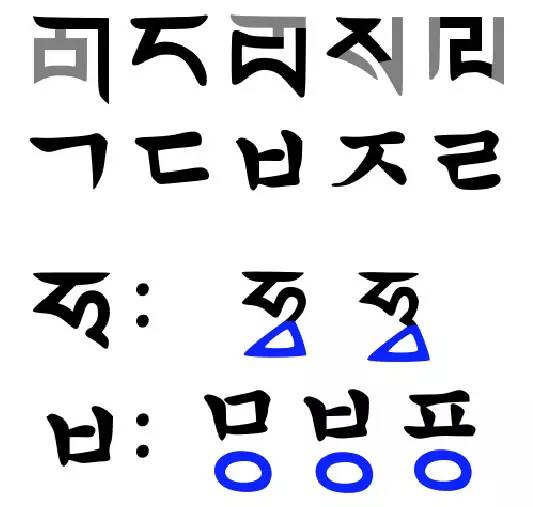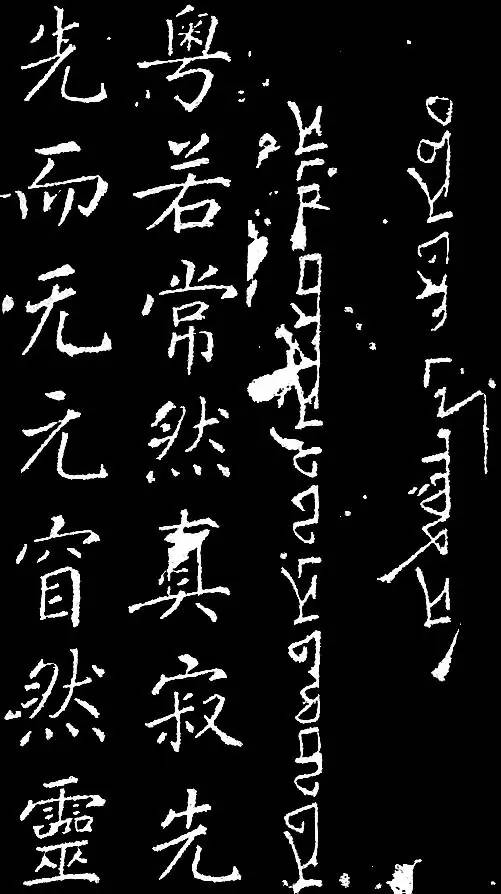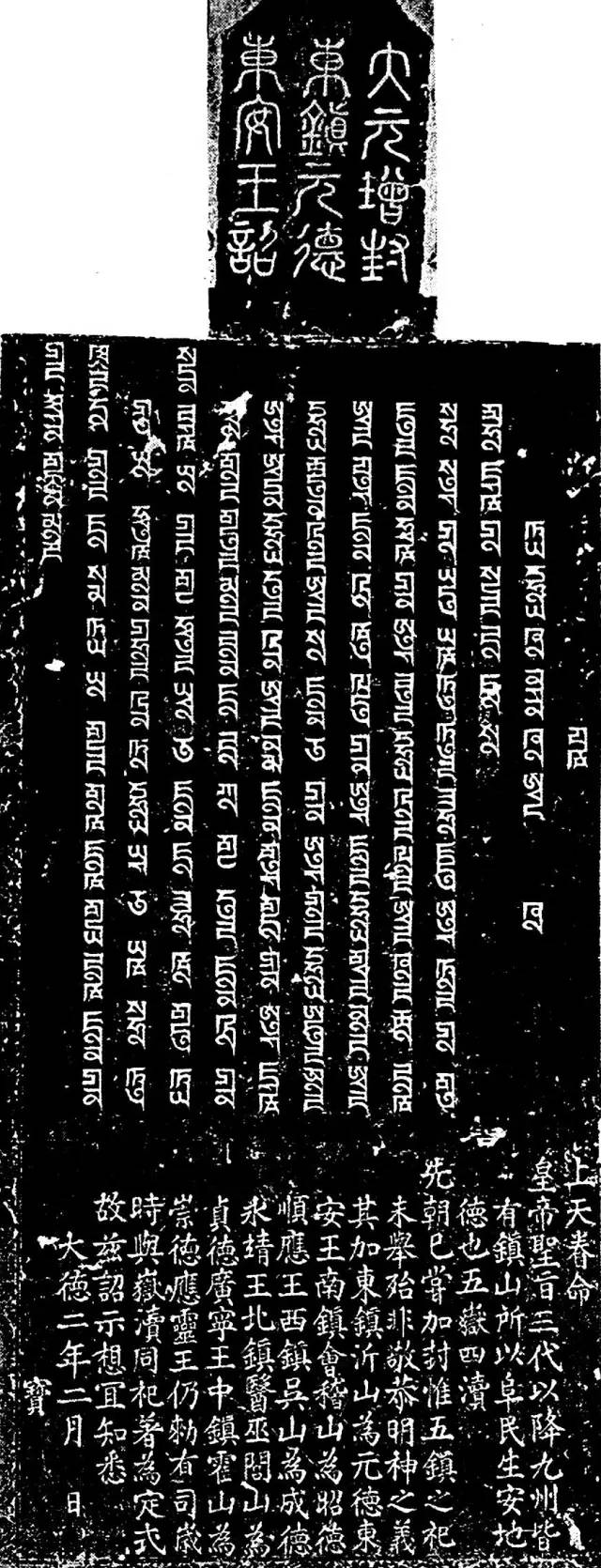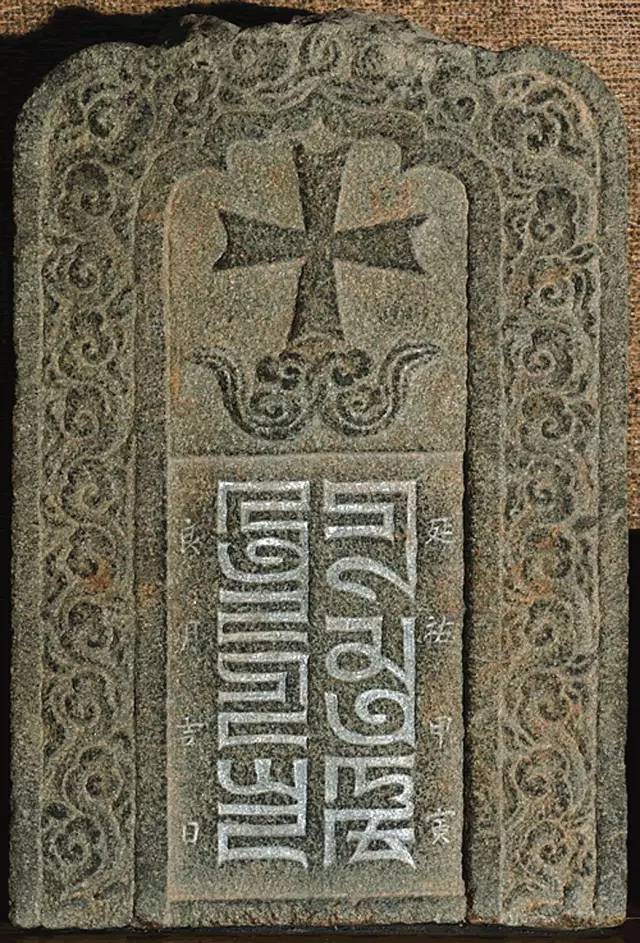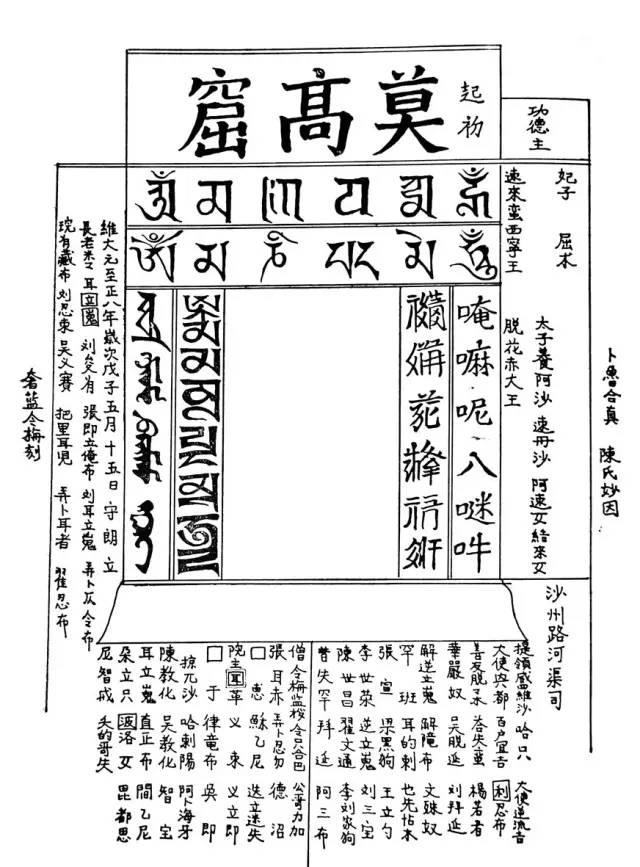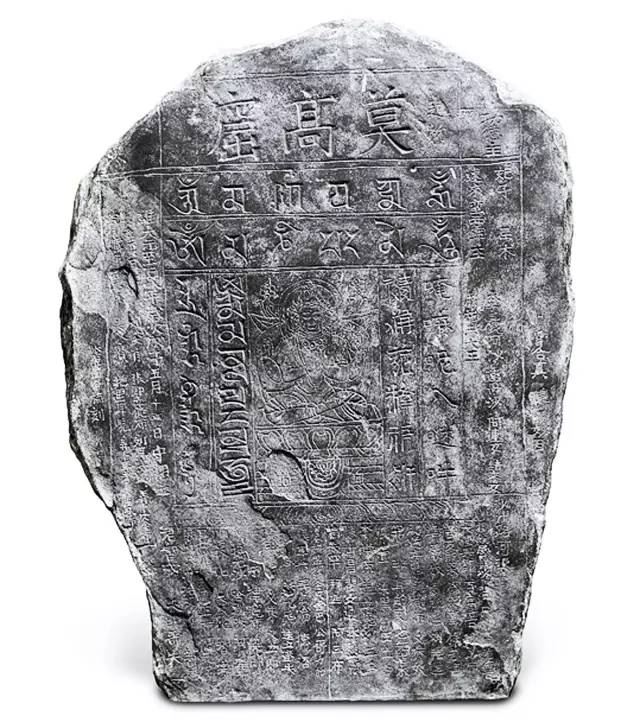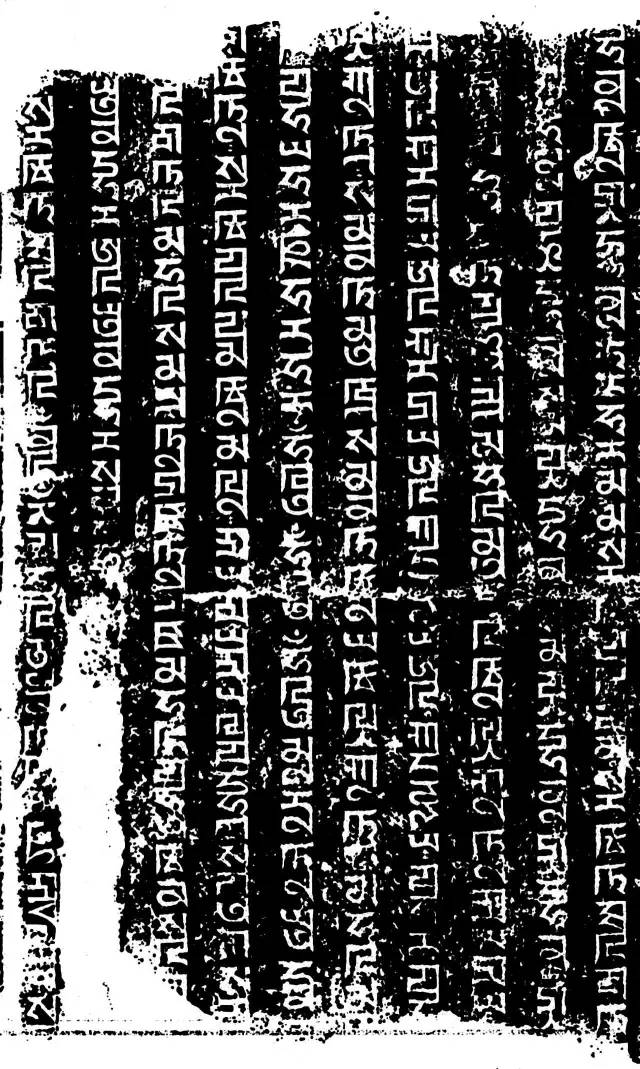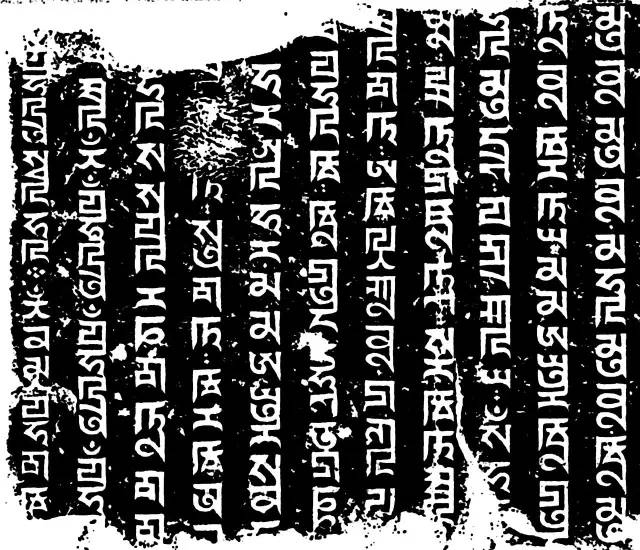
八思巴字(Phags-pa)
{{tag.name}}八思巴字(八思巴字:ꡏꡡꡃ ꡣꡡꡙ ꡐꡜꡞ,轉寫:mongxol tshi,意為「蒙古文字」;蒙古語:дөрвөлжин үсэг,轉寫:dörvöljin üseg,意為「方體字」;藏文:ཧོར་ཡིག་གསར་པ་,威利:hor yig gsar ba,意為「蒙古新字」。)是元朝忽必烈時代由國師八思巴根據當時的吐蕃文字而制定的一種文字,用以取代標音不夠準確的蒙古文字。然而此時橫跨歐亞的蒙古帝國已經分裂為大元和四大汗國各自為政,因此八思巴字一直只有元朝採用,並主要用作為漢字標音符號,所以被語言學家稱為最早的漢語拼音文字。元朝被明朝推翻後,八思巴字還在北元通行過一段時期。到了明末,蒙古高原的蒙古人被其他蒙古民族同化,轉而重新採用蒙古文字。
八思巴字:ꡏꡡꡃ ꡣꡡꡙ ꡐꡜꡞ,轉寫:mongxol tshi,意為「蒙古文字」
八思巴字在書寫上採用字母排列成一個一個類似漢字的方體字,雖然看上去有點類似漢字的印章字,但和漢字表意文字不同,她是表音的文字,比如音譯漢字時會採用字母組成類似漢字的方體造型,這種字母組合方式也影響了後來韓國文字,韓字字母和八思巴字有很大近似度,有部分學者認爲韓字字母其實是受八思巴字影響創制出來的,只是《訓民正音》不願提及罷了。
韓字 한글 (Hangeul)
構造也和八思巴字母一樣
上:八思巴字的k,t,p,s,l字母與韓文的k,t,p,ts,l字母相比較
下:八思巴字的h,w,v,f字母與韓文的w,v,f字母相比較
從設計師的角度看八思巴字是一種很有設計感的字體
下面分享一些八思巴字的圖片
八思巴文蒙古語詔書
大秦景教流行中國碑
翁舍楊氏墓道碑刻ꡖꡟꡃ ꡚꡦ ꡗꡃ ꡚꡞ ꡏꡟ ꡈꡓ (·ung shė yang shi mu taw)
大元增封東鎮元德東安王詔
莫高窟六字真言碑
居庸關雲台八思巴經文
《書史會要》中的八思巴
《事林廣記下》中的八思巴文百家姓
八思巴文牌子